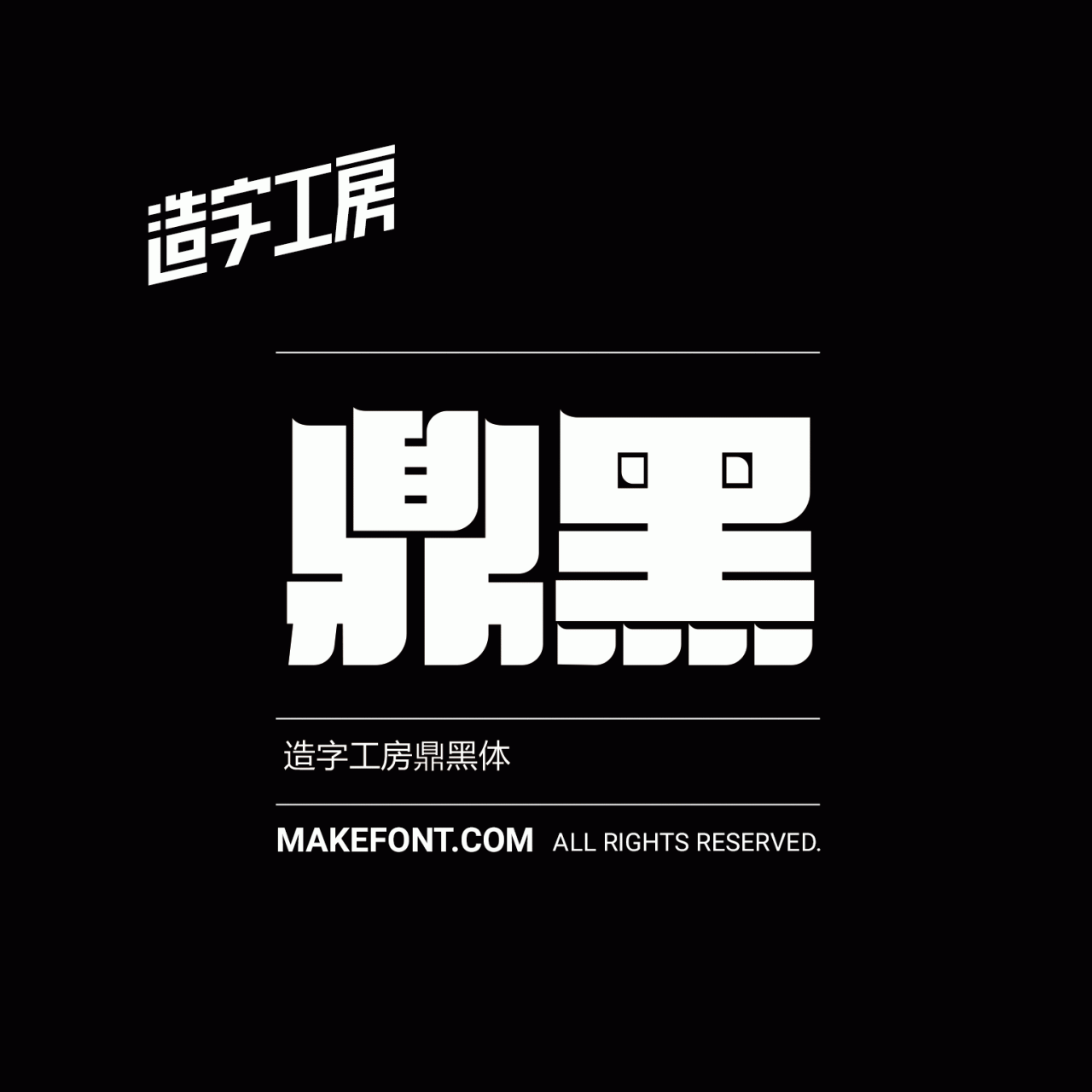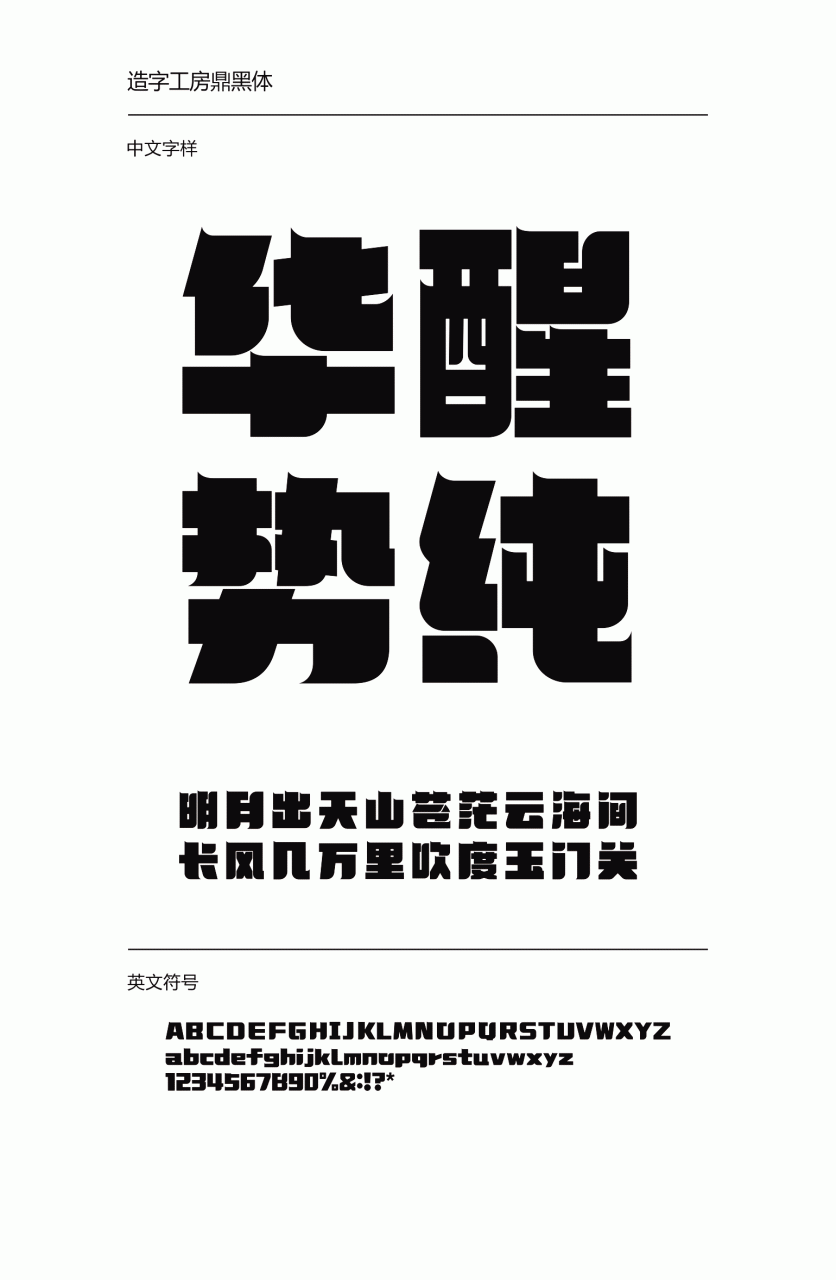
造字工房鼎黑常规体设计说明
造字工房鼎黑体,笔触粗犷厚重,雄阔严整,笔画起承顿挫飘逸流畅,朴拙中不失灵动。适用于大标题、品牌广告宣传等强有力的视觉表现空间环境。 本字体为简体字库,采用OpenType/CID格式,Adobe-GB1-5编码。基于中华人民共和国GB2312-80字符集标准,另按需添加101个汉字。共收容字数6864CJK汉字,ASCII常用字符100个。